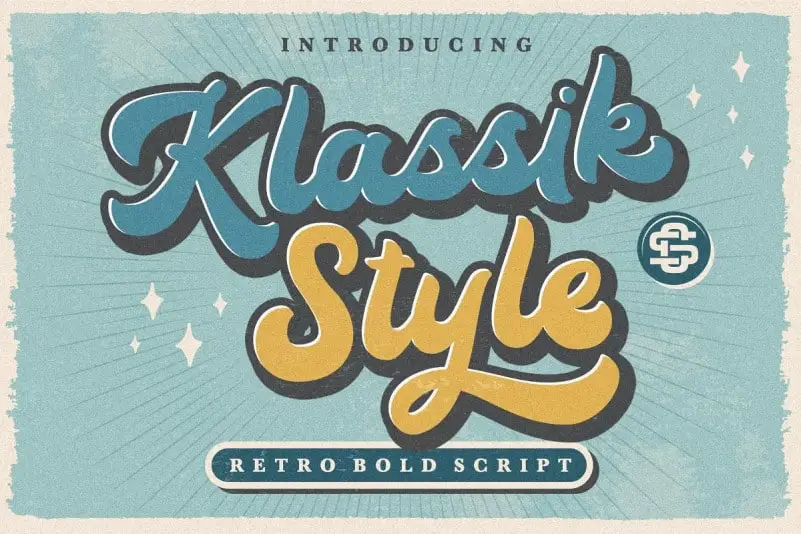
A Klassik Style Script Font é uma tradição bold script que tem raízes no cultivo cultural de pintura de sinais norte-americana. Essa elegante fonte, disponível em alternativas contextuais e alternativas swash para cada letra padrão, oferece um toque de charme retro para qualquer projeto gráfico. Suas alternativas contextualizadas garantem ligações suaves e fluidas, enquanto as alternativas swash adicionam um toque sofisticado e personalizado a seus trabalhos. Com uma forte conexão à cultura das placas de sinalização, a Klassik Style Script é perfeita para uma variedade de aplicativos que buscam um toque de escrita manual – seja para identidade de marca, logotipos, decorações de casamento, postagens nas redes sociais, anúncios, embalagem de produto, design de produto, etiquetas, fotografias, marcas de água ou convites. Esta fonte traz um toque autêntico à sua criação.